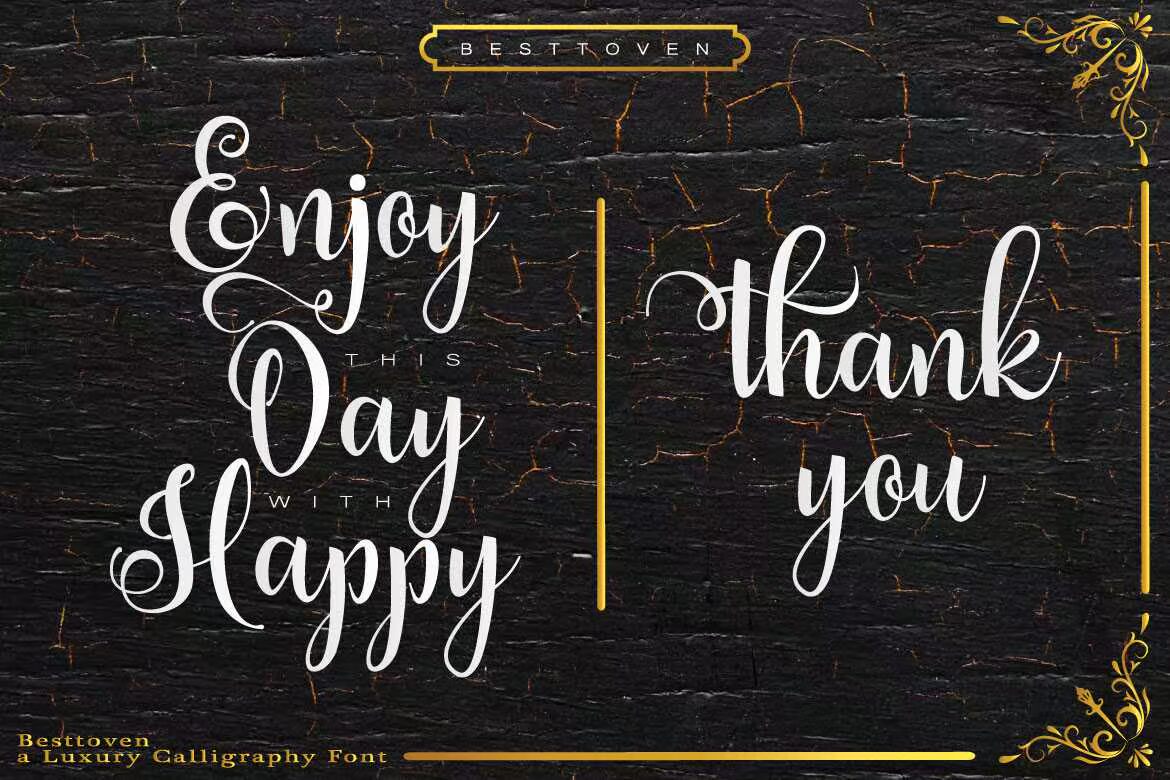
Best To Venisam现代书法艺术中心,拥有完美的奢华。Best To Venisam现代书法艺术中心非常适合您的所有业务和项目设计,包括品牌、徽标、婚礼活动、签名、室内设计、海报、报价、电影等等。Best To Venisam现代书法艺术中心,完美奢华。最适合您的所有业务和项目设计,包括品牌、徽标、婚礼、签名、室内设计、海报、报价、电影等等。